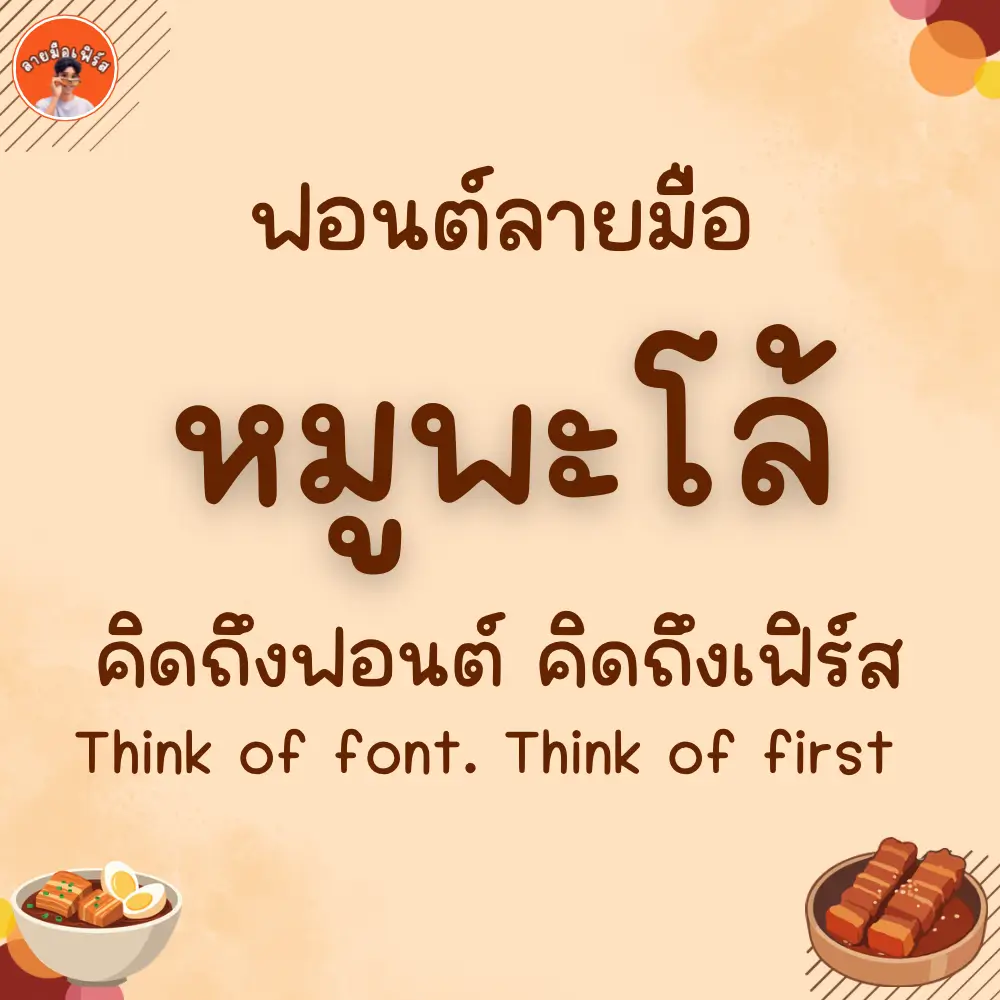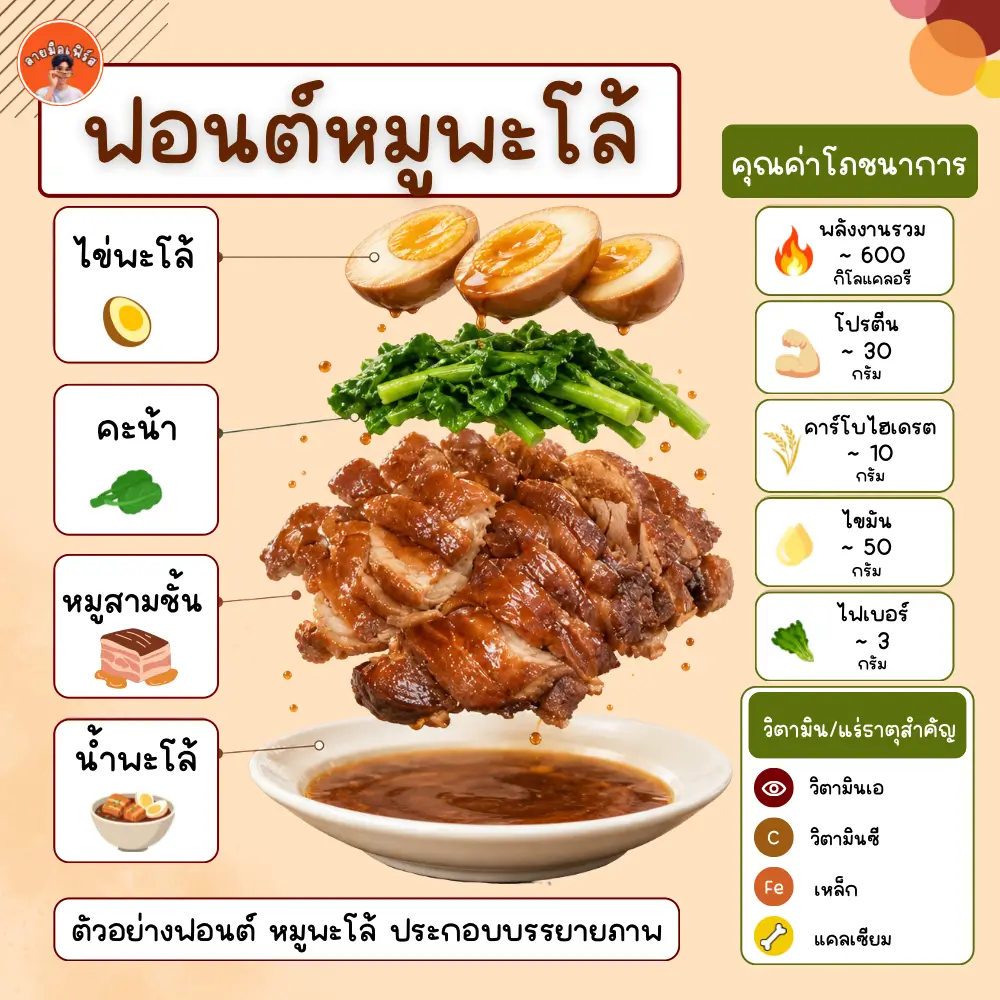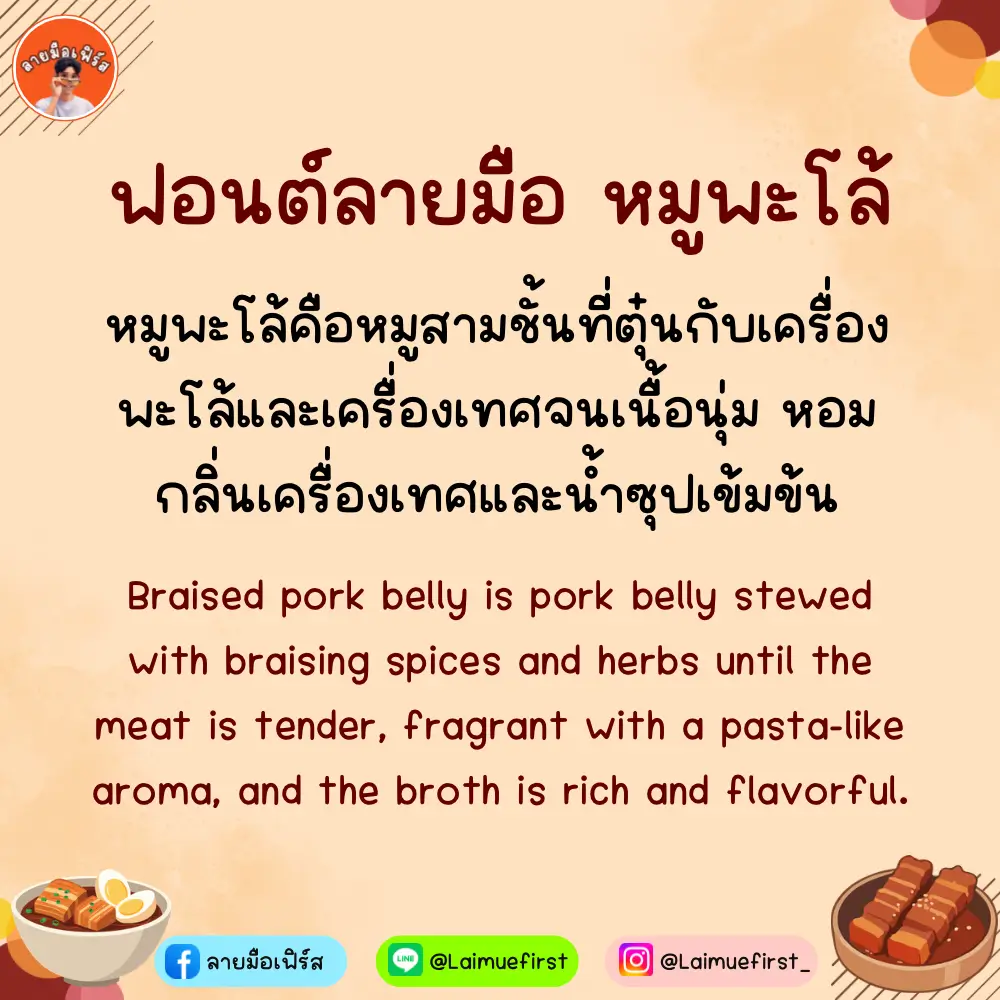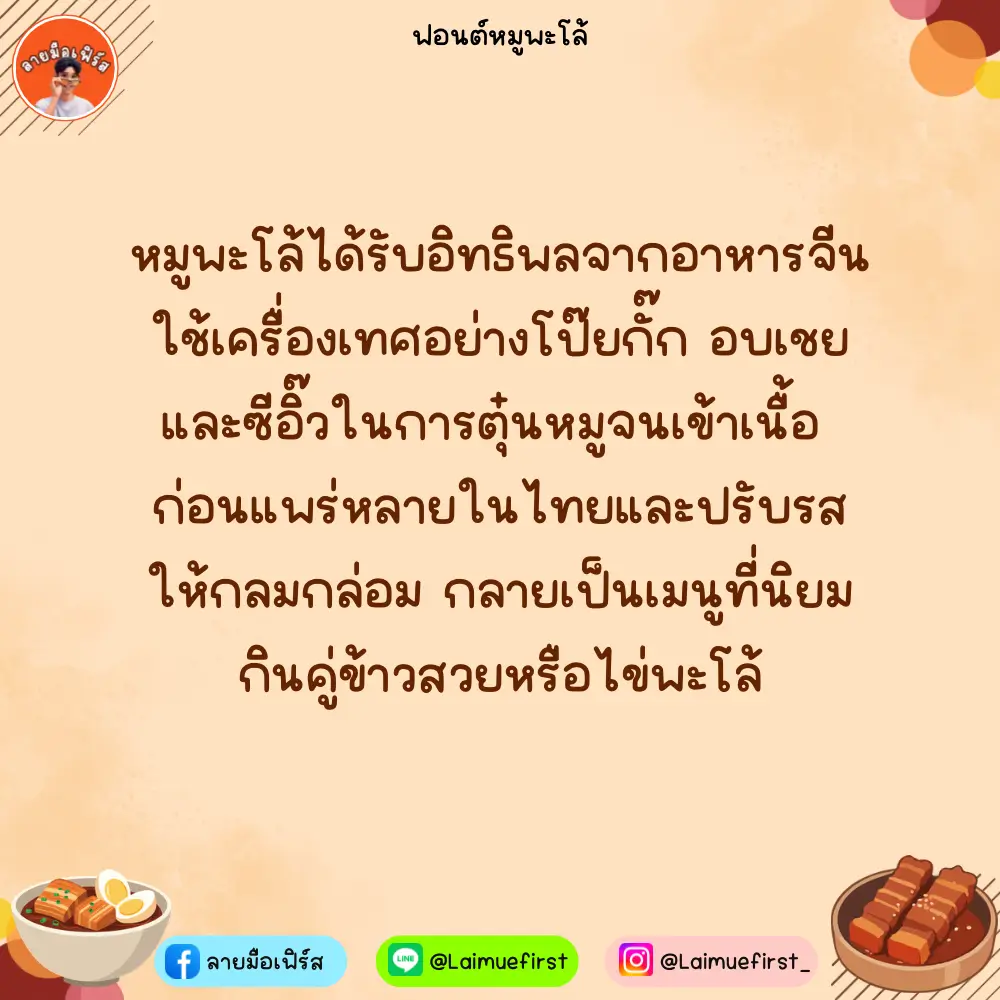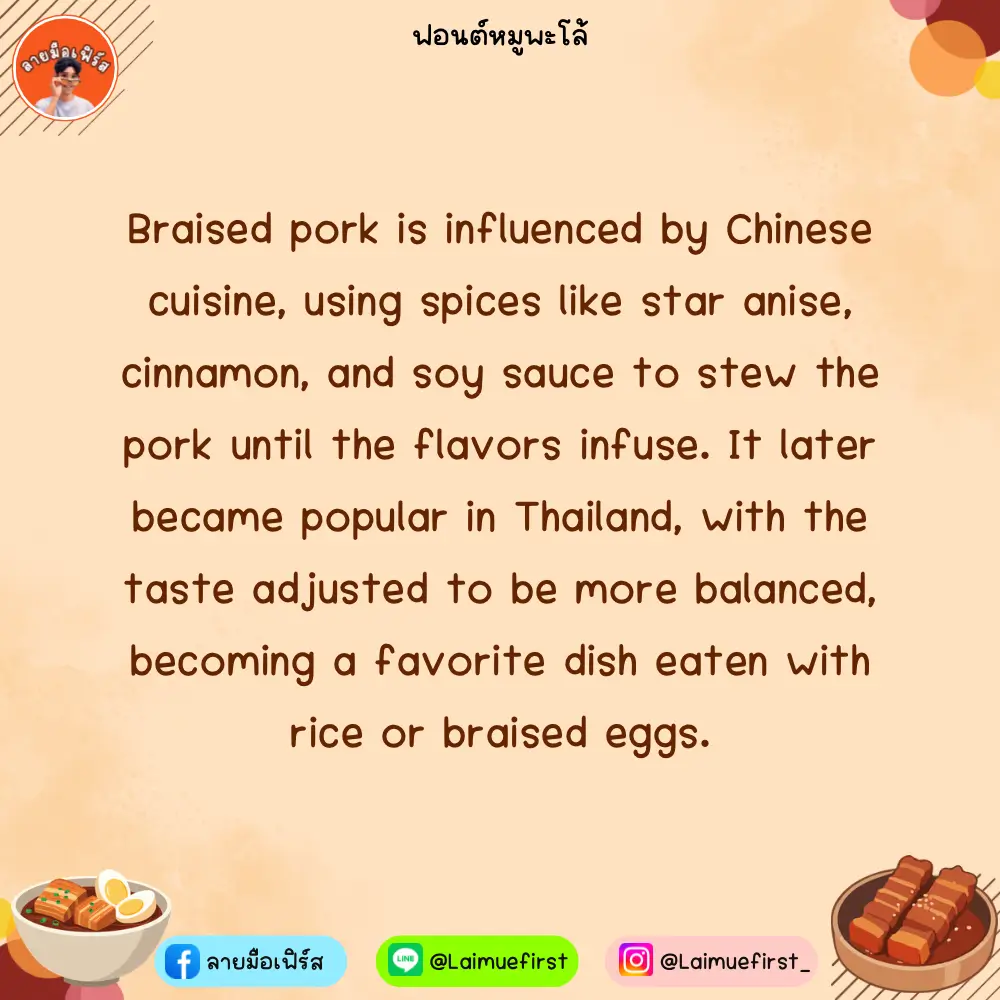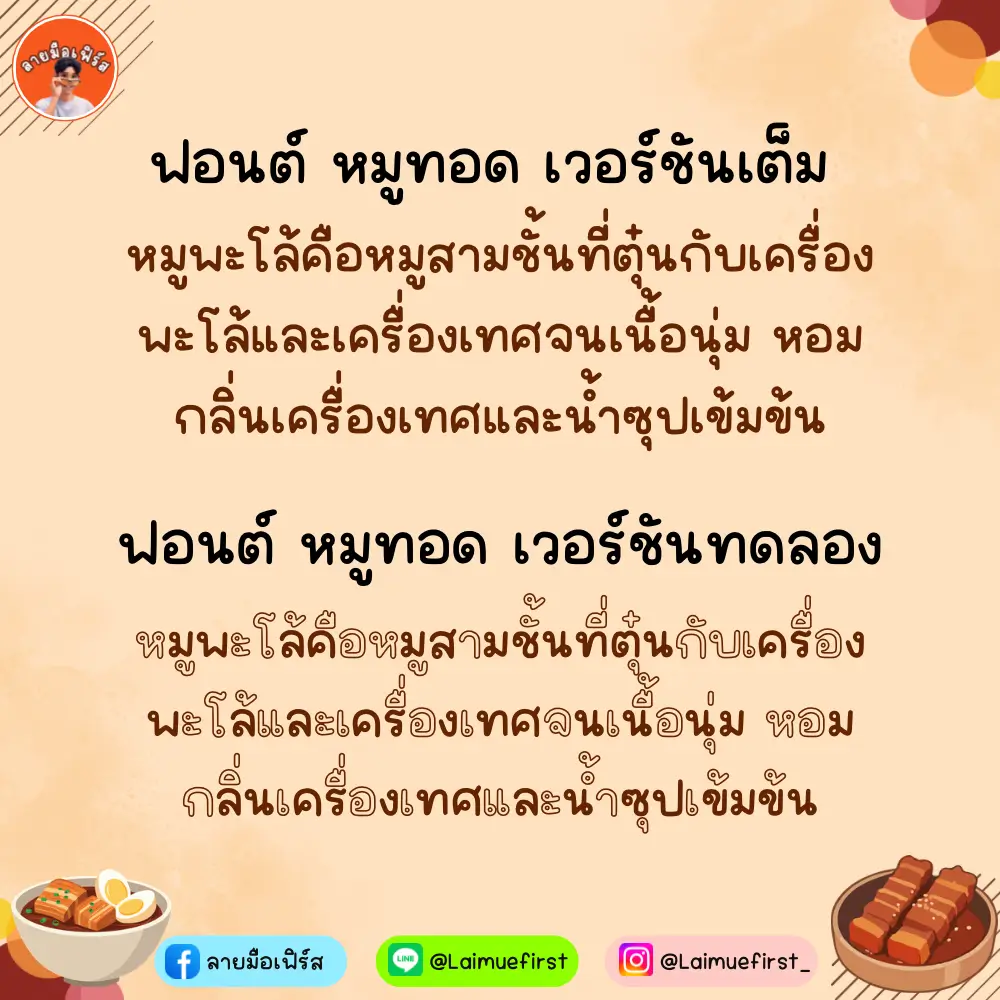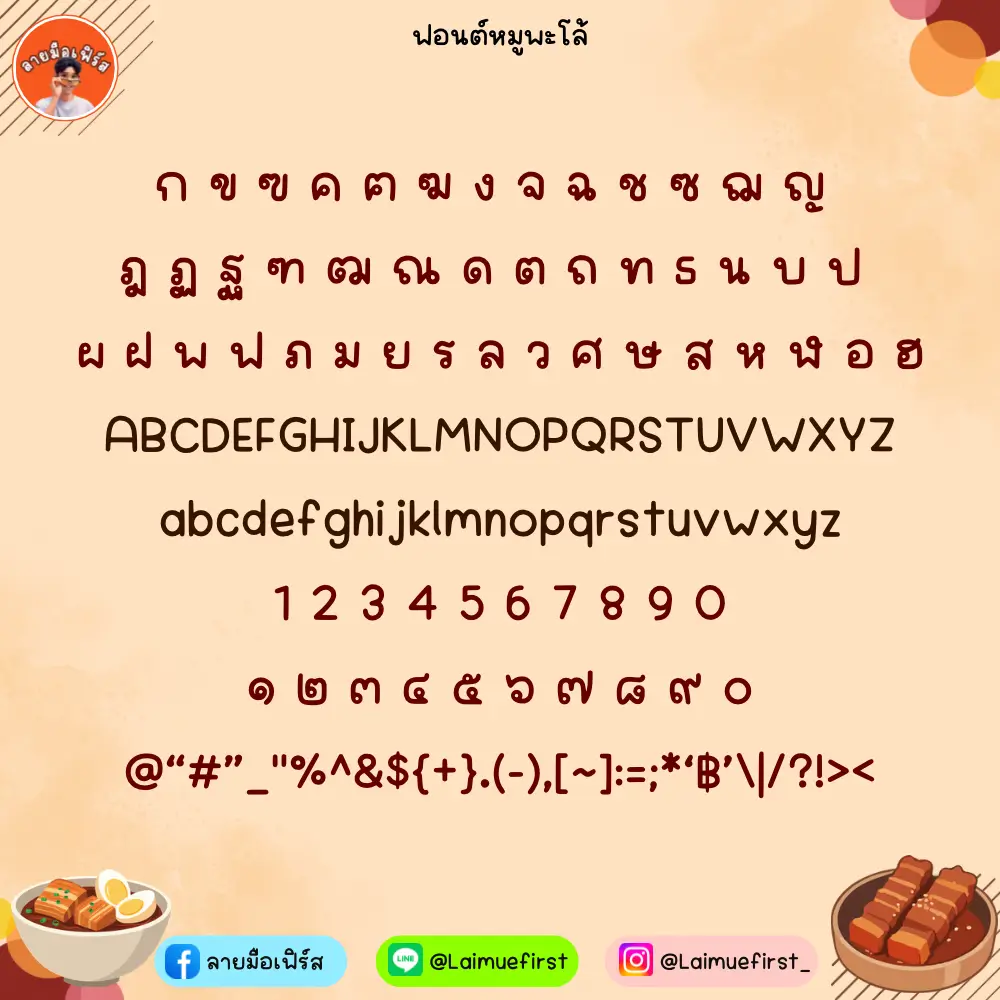
ฟอนต์ลายมือ หมูพะโล้ (LMF Moophalo) – แจกฟรีสำหรับทดลองใช้งานแบบส่วนตัว เวอร์ชันทดลอง (Demo)
- ตัวหนังสือปกติ ไม่มีตัวโปร่งปน
หมูพะโล้ (LMF Moophalo)